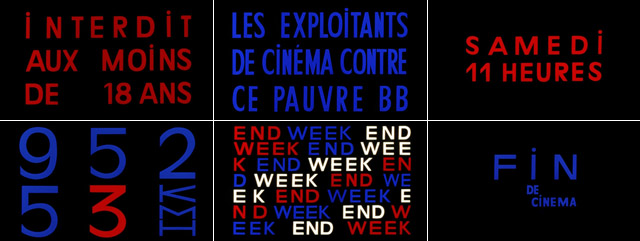
La tipografía de Jean Luc-Godard
Los títulos de crédito forman parte de un sistema que refleja y acompaña el clima de la película. Se los podría considerar como una parte integrante del conjunto de la obra, pero también se los podría considerar como una obra ligada al producto audiovisual autónoma.
Jean Luc-Godard fué uno de los miembros de la llamada “Nouvelle Vague” y uno de los mayores precursores del cine de vanguardia, del humor ácido y de una edición y narración contemporáneas, poco o nada convencionales para su época.
El universo de los títulos de crédito se ha llegado a convertir en una rama del séptimo arte, hasta el punto de haber agencias de motion graphics especializadas en esta disciplina como es el caso de Digital Kitchen o Imaginary Forces.
Se han localizado casi todas las películas de la primera parte de la carrera de Godard y todas las imágenes fijas que contienen tipografía: títulos de las secuencias de títulos de apertura, intertítulos y títulos finales. Al igual que las películas mudas, Godard utiliza un montón de intertítulos, que hacen sus películas mucho más tipográficas que otras películas de los años 60 y los años 70.
La importancia de los títulos de crédito y de la tipografía en cineastas como Hitchkock o Godard es indiscutible y no puedo concebir una clase de cine en la que no se haga un extenso review del trabajo de artistas como Saul Bass (diseñador gráfico y creador de algunos de los créditos mas representativos de la historia del cine), que tanto se esta recordando en los últimos años de manera más que merecida.
El estudio Atelier Carvalho Bernau ofreció gratuitamente hace unos meses una maravillosa tipografía para celebrar el cumpleaños nº80 del director francés.  La tipografía estuvo inspirada en la secuencia de títulos de las películas de Godard ‘Made in U.S.A’ (1966) y ’2 ou 3 choses que je sais d’elle’ (1967)
Es interesante observar a los diseños evolucionar. En esta era digital es estimulante ver tipografía que no está hecha desde la computadora: la apariencia imperfecta y hecha a mano de las letras o la rara capital de la letra I. Incluso cuando utiliza una fuente existente, como Antique Olive en ‘Week End‘ (1967), las formas de las letras se ven como si fueran recortadas.
‘Sauve qui peut (la vie)’ (1980) es la última película cuyos títulos de créditos fueron hechos de manera personalizada. En sus últimas películas Godard utiliza tipografías existentes, como Futura, Univers, Helvetica y Garamond.
Si hay algo del mundo cinematográfico que me produzca mayor fanatismo que el celuloide en sí, son estos títulos de crédito.